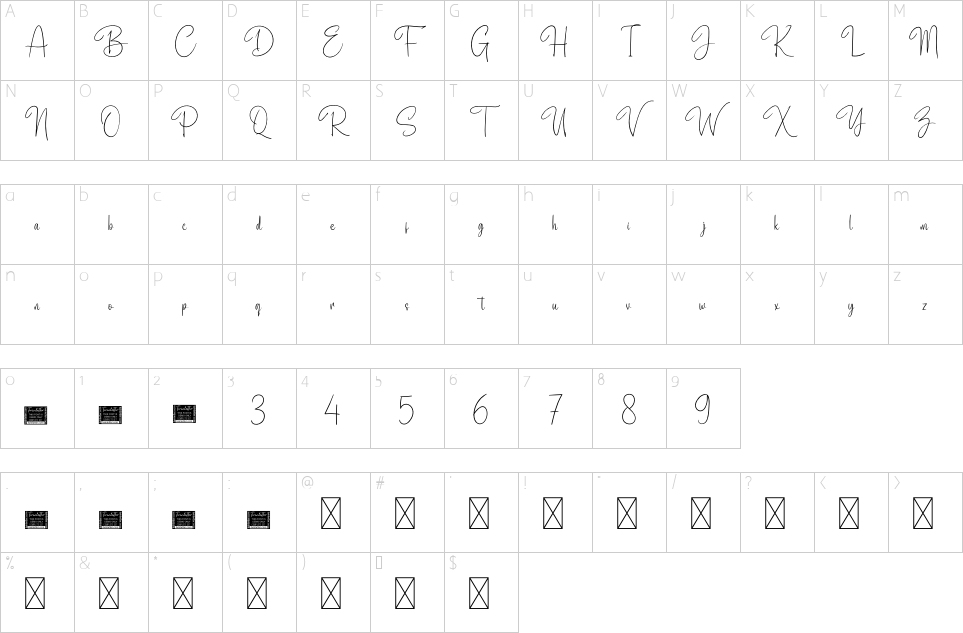
Adigussto Font – Download Grátis
Descubra a Adigussto font, uma elegante e sofisticada opção para seus projetos digitais. Desenvolvida por rozi, esta fonte oferece um toque de modernidade para qualquer projeto, seja em seu website, app móvel ou aplicação de design. O Adigussto foi projetado para dar um toque único a qualquer projeto, combinando perfeitamente com outros tipos de fontes para criar um layout visualmente agradável e profissional. Com um design minimalista e moderno, a Adigussto é uma escolha perfeita para designers que valorizam a simplicidade e a funcionalidade. Com um design cuidadosamente pensado e um download de 1.789 vezes, você pode garantir que seu projeto está impecavelmente equipado. Em uma categoria de fontes gratuitas, o Adigussto é uma excelente adição para qualquer designer que busca uma fonte única e versátil.